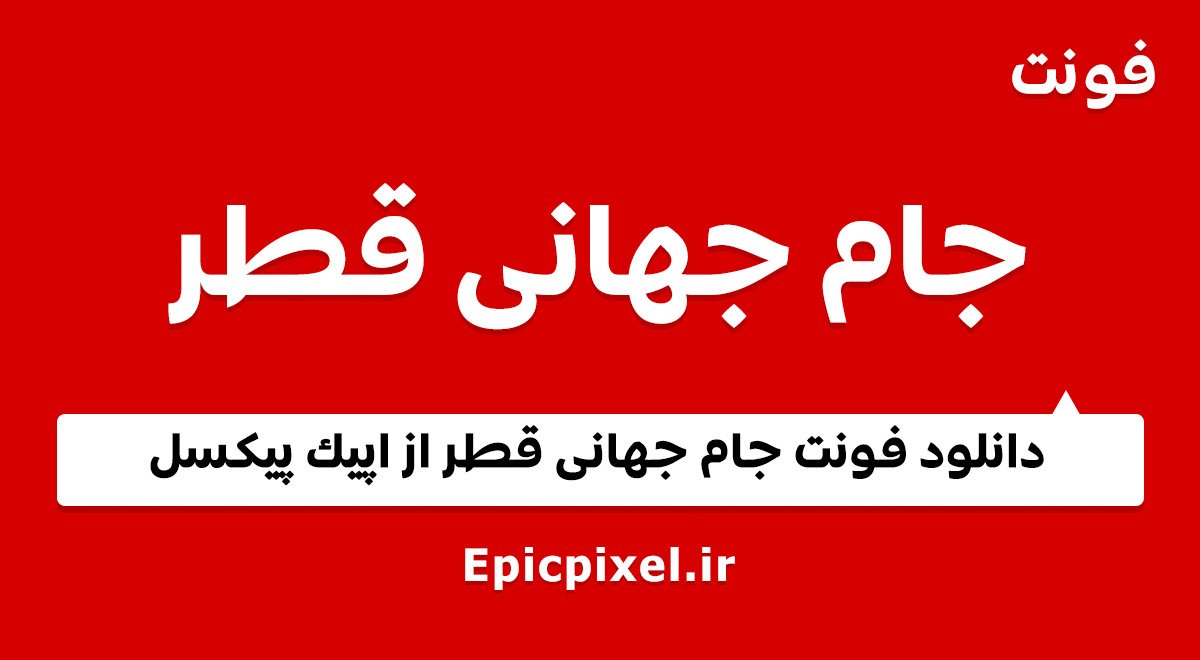
فونت جام جهانی قطر عربی فارسی
برای ایجاد طرح ها و نوشته های جذاب و مرتبط با جام جهانی قطر ۲۰۲۲، می توانید فونت رسمی این مسابقات را به صورت رایگان دانلود کنید. این فونت با طراحی خاص و الهام گرفته از فرهنگ منطقه، به شما امکان می دهد تا طرح هایتان را با هویت بصری جام جهانی متمایز کنید و به آن ها جلوه ای حرفه ای و منحصر به فرد ببخشید.